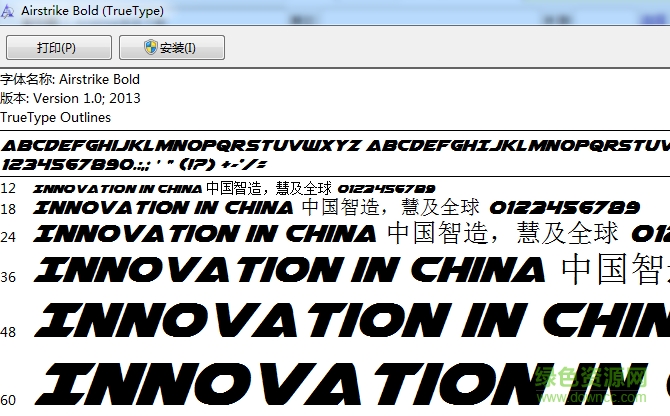
Airstrike blod字體
Airstrike字體是英文字體庫中的個性字體,該字體能夠?yàn)橛脩籼峁O具個性的效果,幫助用戶快速在別人心里留個非常深刻的印象,有喜歡的朋友就來綠色資源網(wǎng)下載使用吧!
Airstrike字體是一款個性英文字體,字體非常適合用于平面設(shè)計(jì)行業(yè),有需要的朋友就趕快來綠色資源網(wǎng)下載吧!